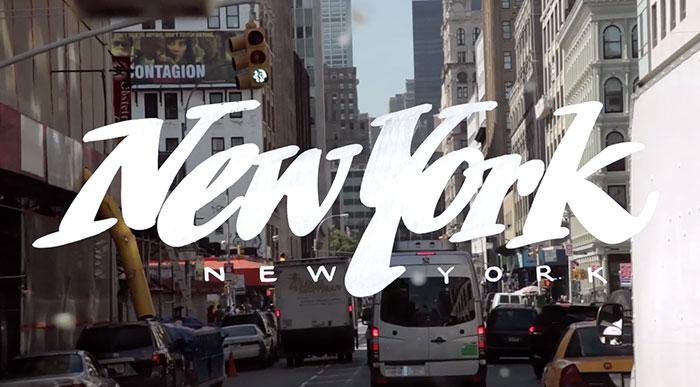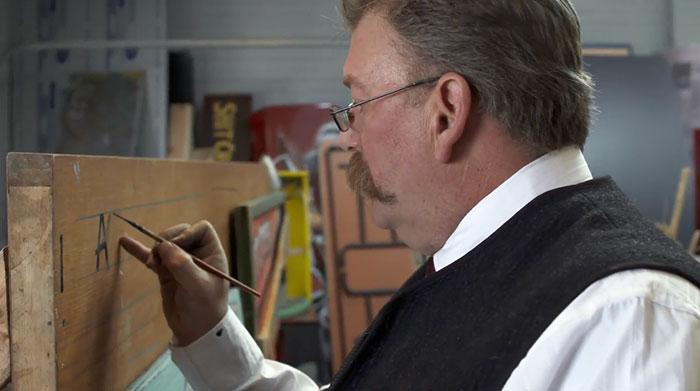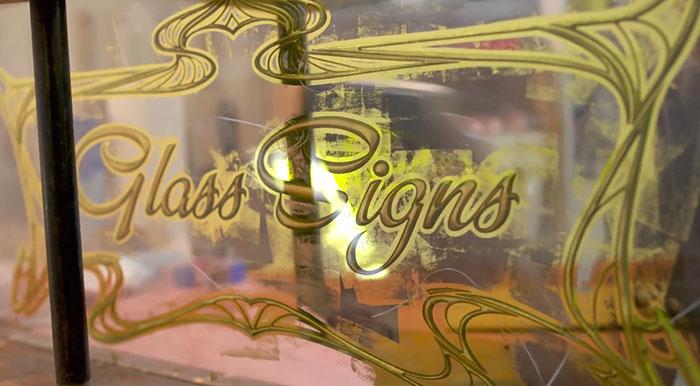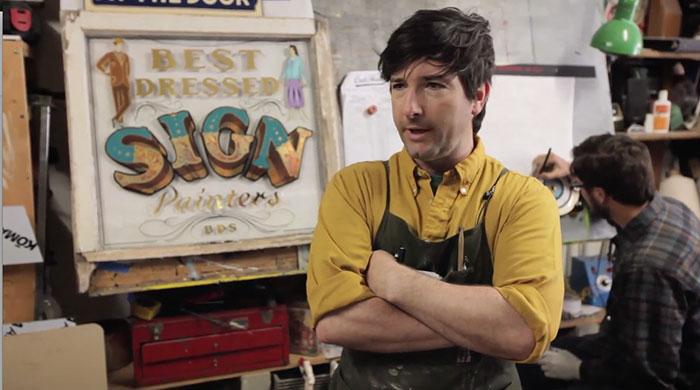
Schildermaler-Dokumentarfilm »Sign Painters« erschienen
Der Film »Sign Painters« von Faythe Levine und Sam Macon beleuchtet die gut 150-jährige Geschichte der Schildermalerei in den USA. Die mehr als einstündige Dokumentation portraitiert einige der noch aktiven Schildermaler-Werkstätten und lässt deren Schildermaler ihre persönlichen Geschichten und die ihrer Zunft erzählen. Natürlich wird auch die Verdrängung der Schildermalerei durch Folienplotts thematisiert.